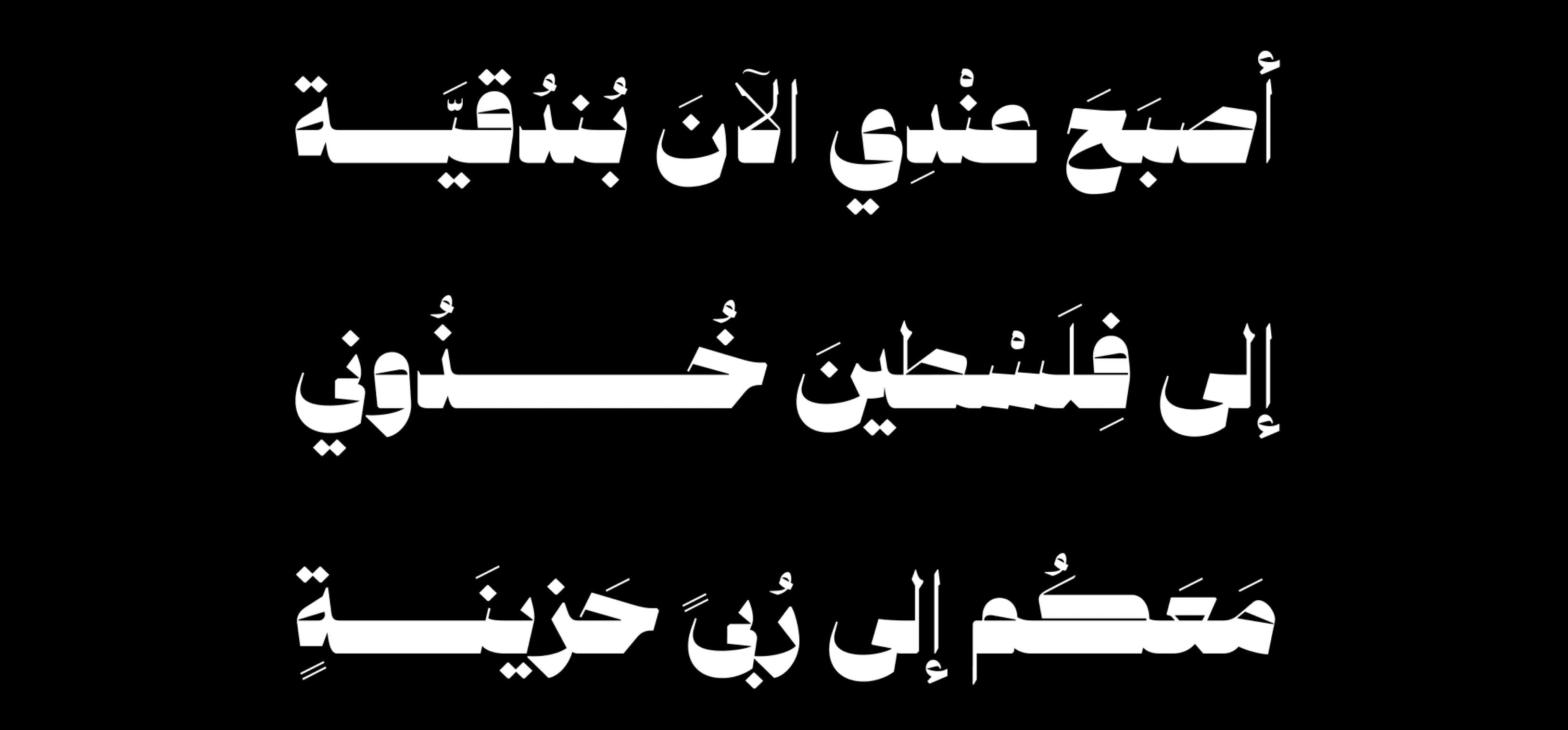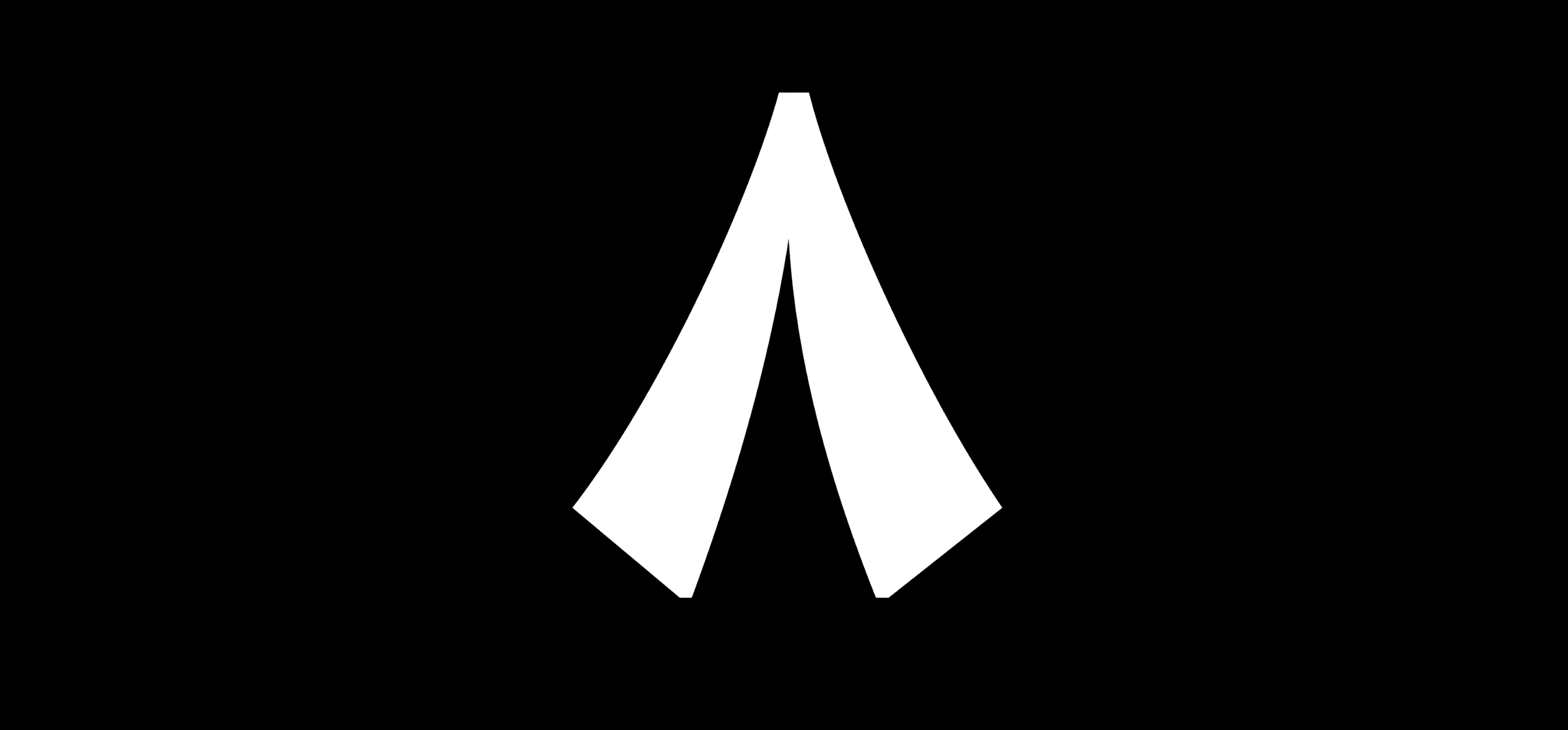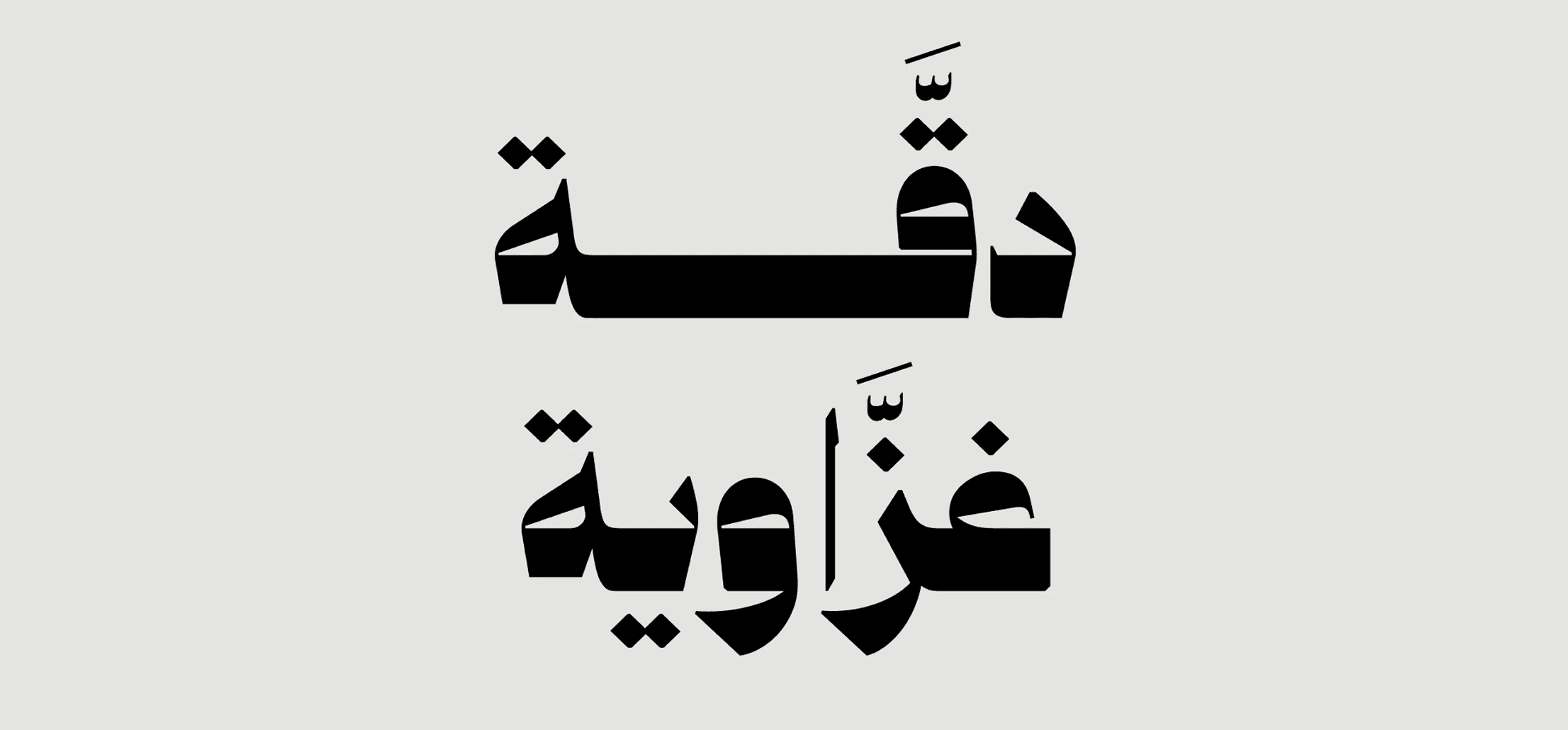
خط عربي عصري وجريء، يتميز بحواف حادة وتباين بصري قوي يمنح الحروف طابعًا مسطّحًا وهندسياً فريداً.
يمزج بين الحداثة والتجريب في تصميم الحروف، ما يجعله مناسبًا للتصاميم الإبداعية، العناوين اللافتة، والأعمال التي تتطلب طابعًا فنيًا مميزًا.
يتوفر بأربعة أنماط مختلفة، ويوفر توازنًا بصريًا فريدًا بين الكتلة والمساحة.